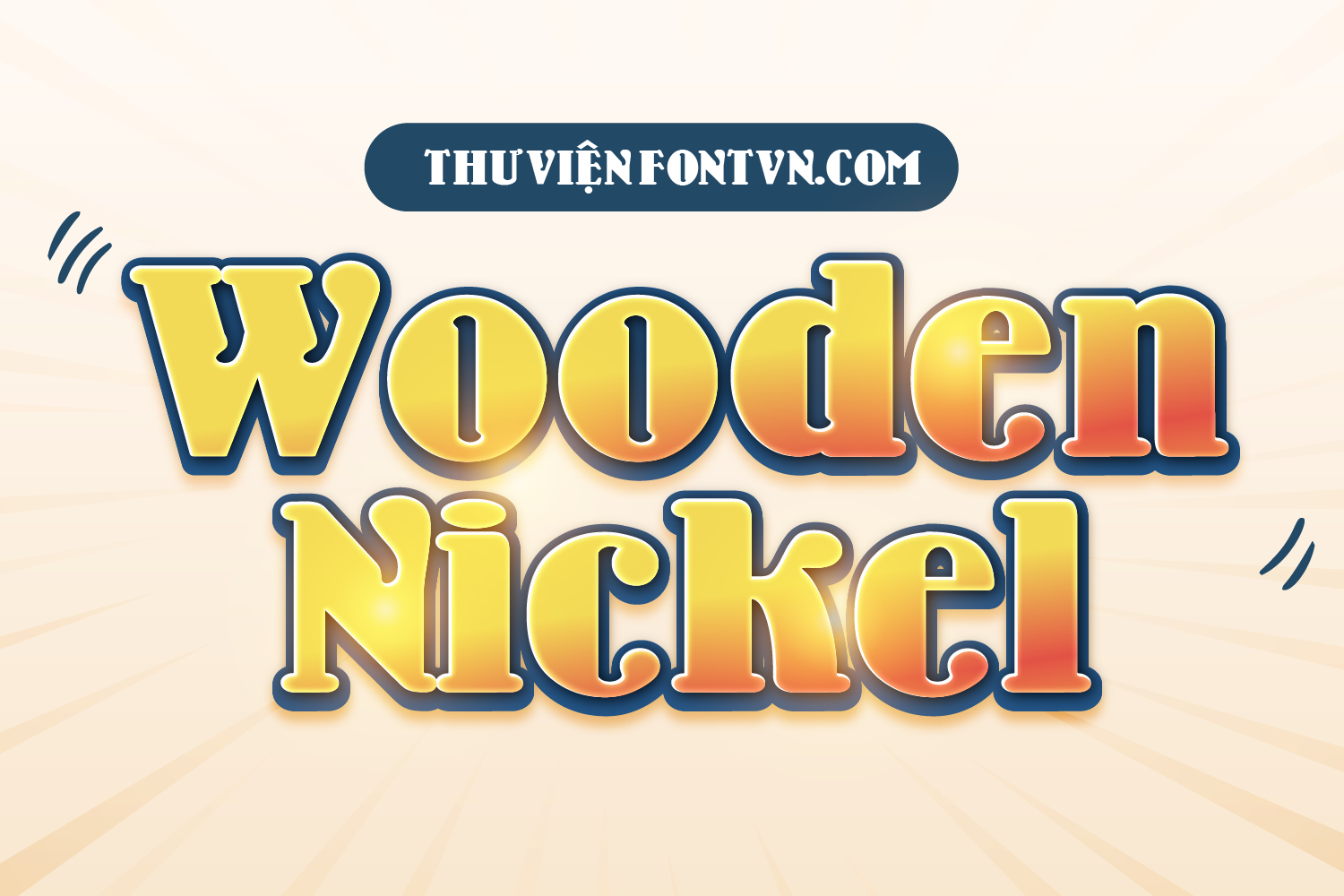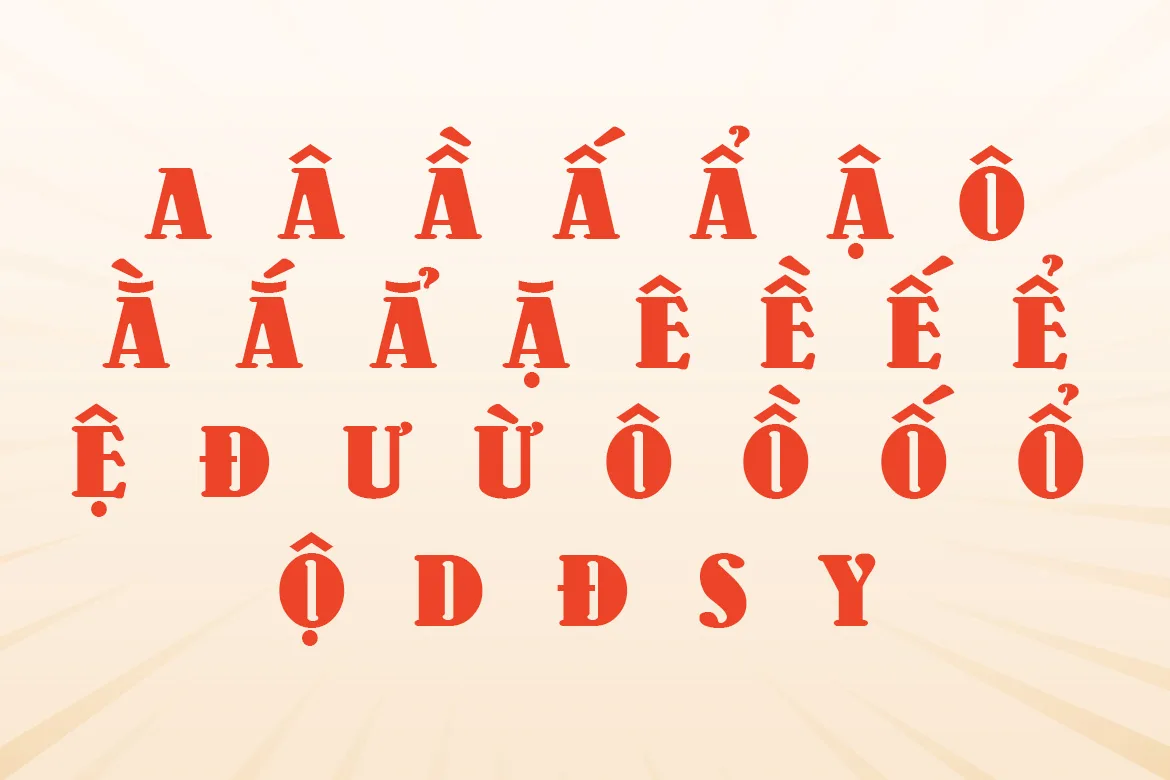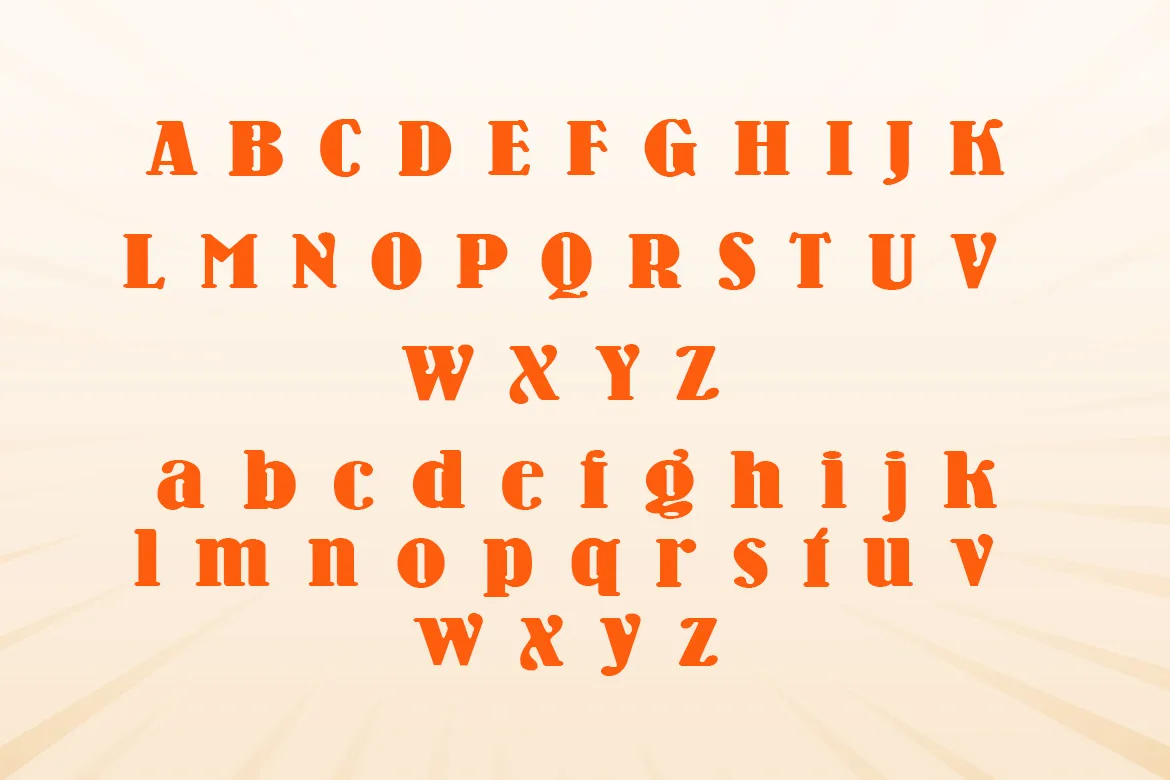
DVN Wooden Nickel Black Việt hóa – Font chữ đậm và phá cách
DVN Wooden Nickel Black Việt hóa là một font chữ đậm, phá cách với phong cách retro vui nhộn, rất phù hợp cho các thiết kế mang hơi hướng hoài cổ nhưng vẫn hiện đại và sinh động.
Font có thân chữ tròn trịa, đường nét to bản, kết hợp với hiệu ứng bóng đổ dày giúp chữ nổi bật mạnh mẽ trên nền sáng hoặc tối. Điểm đặc trưng là các đầu nét bo tròn và phần khoảng hở bên trong chữ được xử lý khéo léo, tạo cảm giác mềm mại nhưng vẫn giữ được sự chắc chắn.